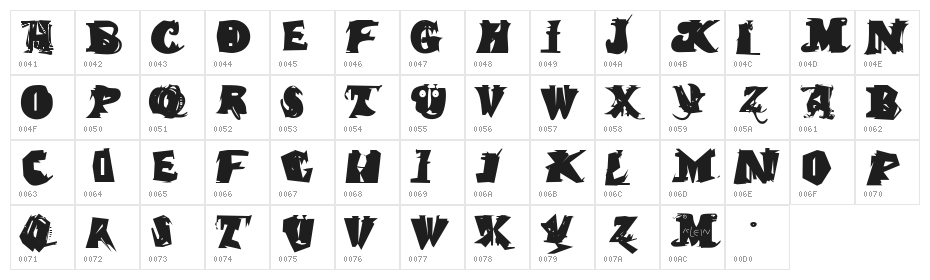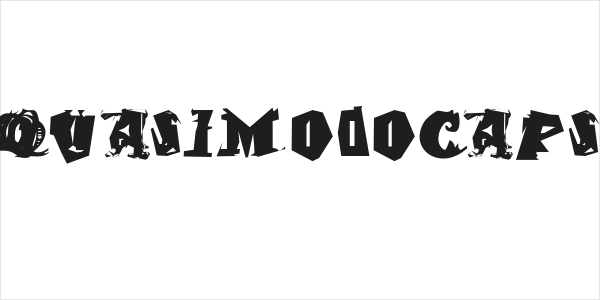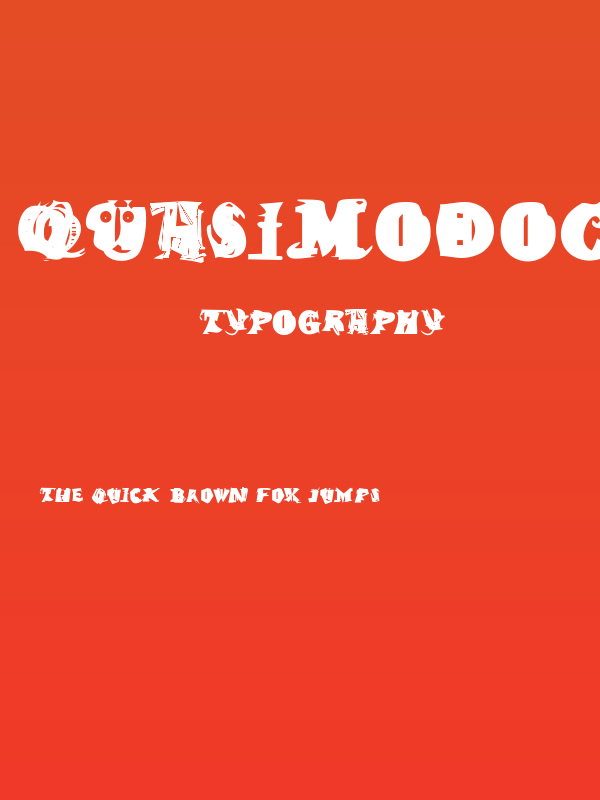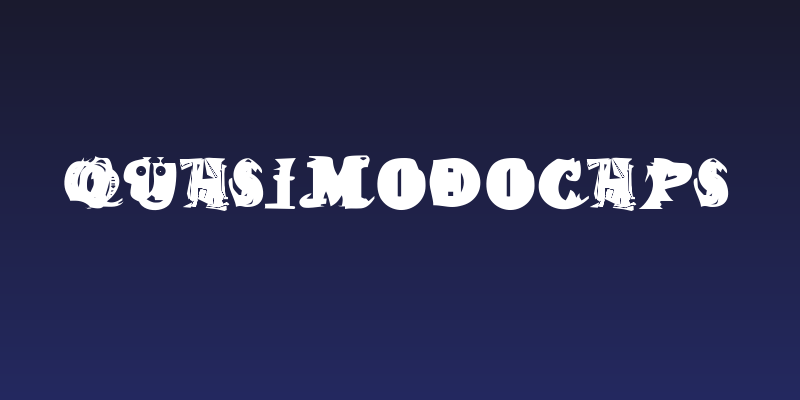
QuasimodoCaps Font
| Vorgeschlagene Projekte | Ideal for album covers, posters, video game titles, or any project requiring a dramatic and artistic flair. |